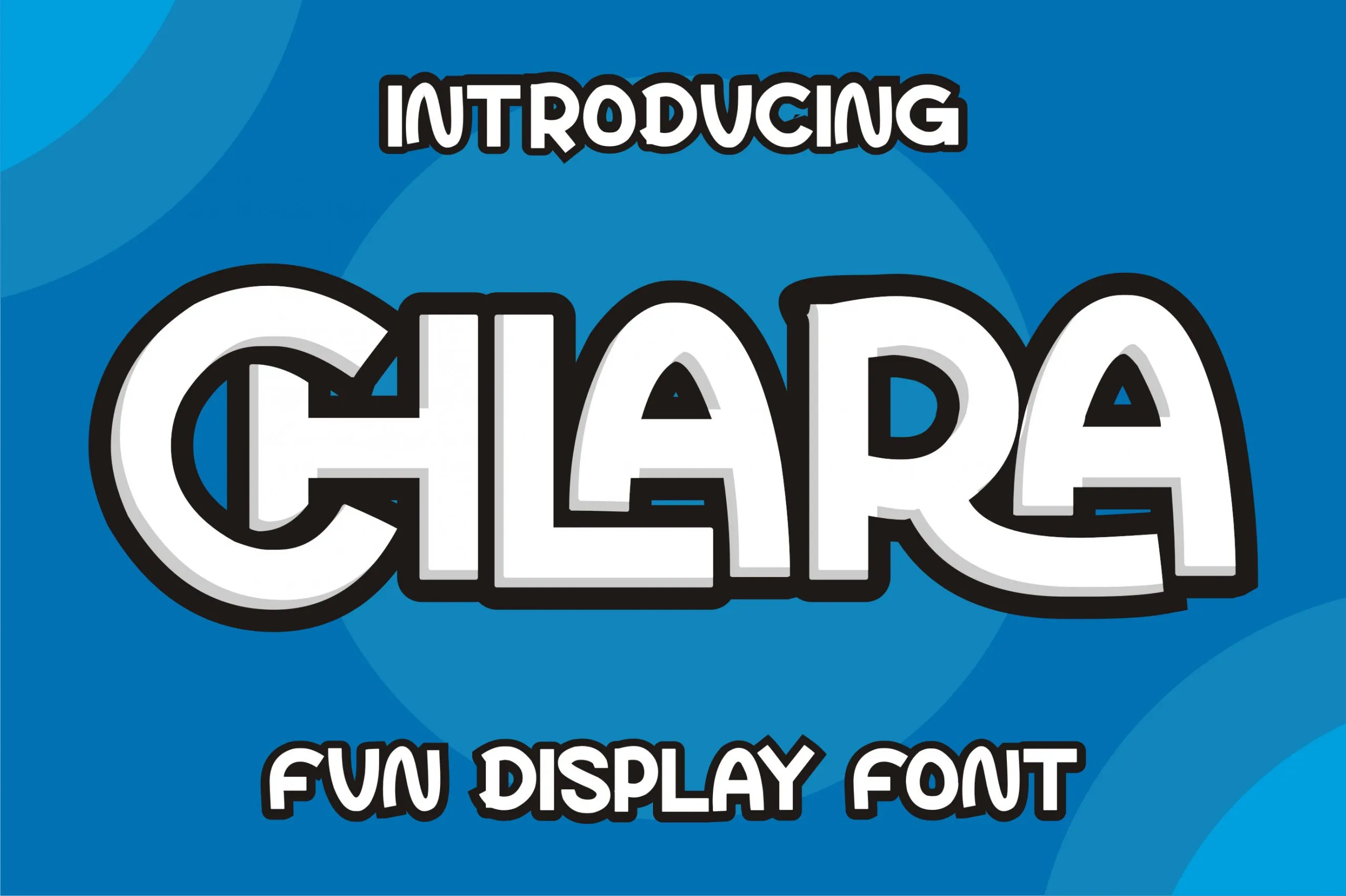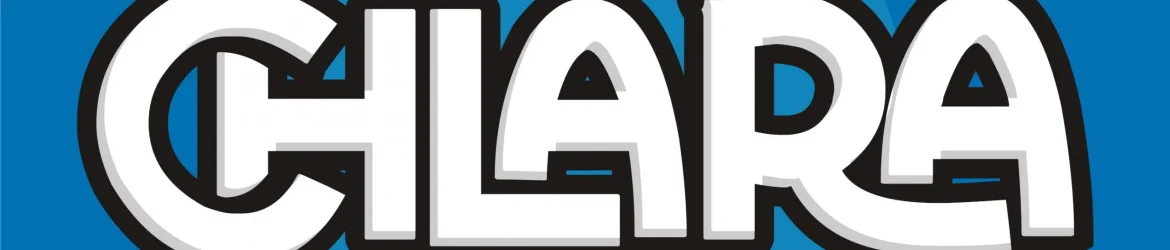
Chlara Display Font – Download Grátis
A fonte Chlara Display é uma escolha ideal para aqueles que buscam um look contemporâneo e atraente para seus projetos visuais. Essa elegante tipografia é especialmente apropriada para gráficos de destaque, headlines e elementos mais chamativos em designs, como banners ou cartazes. A característica mais notável da Chlara Display é seu PUA (Private Use Area) encoded, o que lhe dá acesso direto a todos os caracteres e swashes. Isso significa que você pode explorar uma ampla gama de opções, incluindo formas alternativas e combinações interessantes sem precisar de nenhuma ferramenta adicional. Ideal tanto para designers profissionais quanto iniciantes, a Chlara Display é uma fonte versátil que irá certamente brilhar em qualquer projeto. Seja você um designer gráfico, uma marca ou até mesmo um criador de conteúdo online, essa fonte estará pronta para trabalhar com você para criar resultados memoráveis.